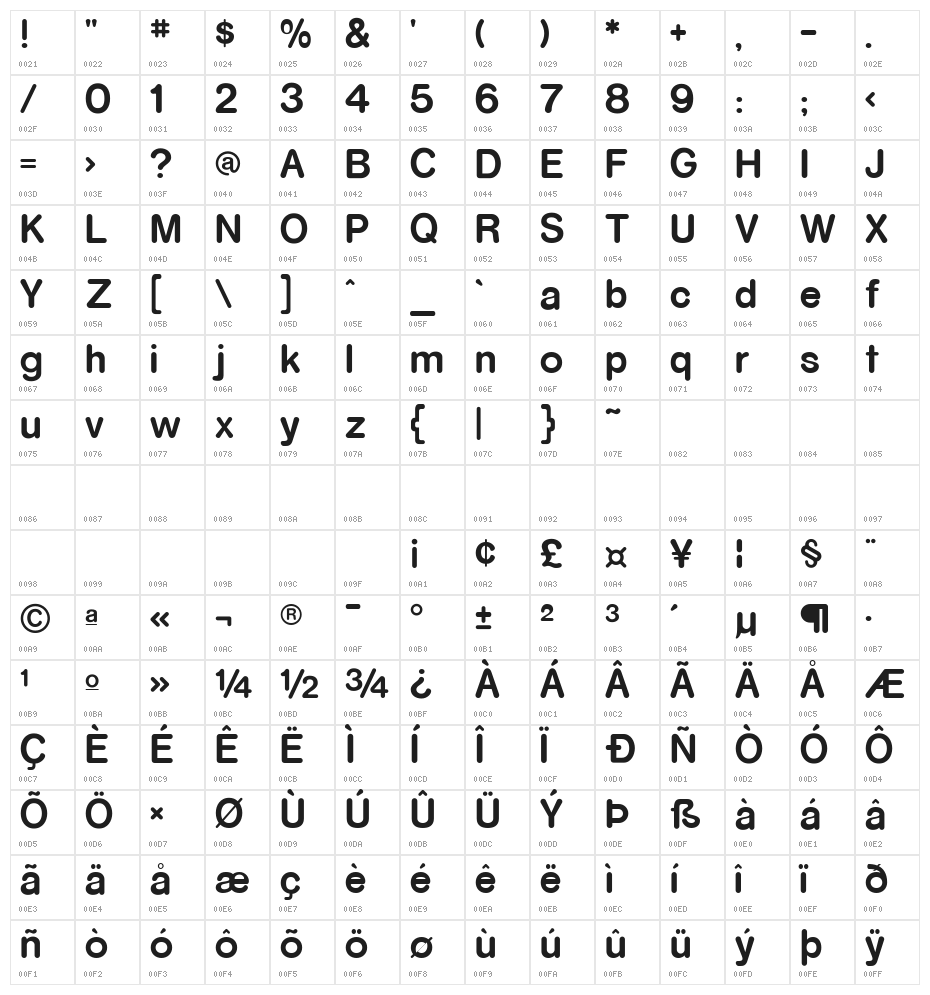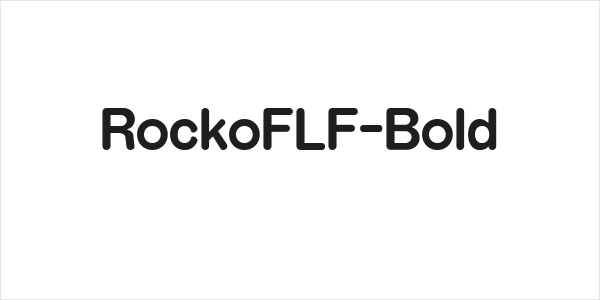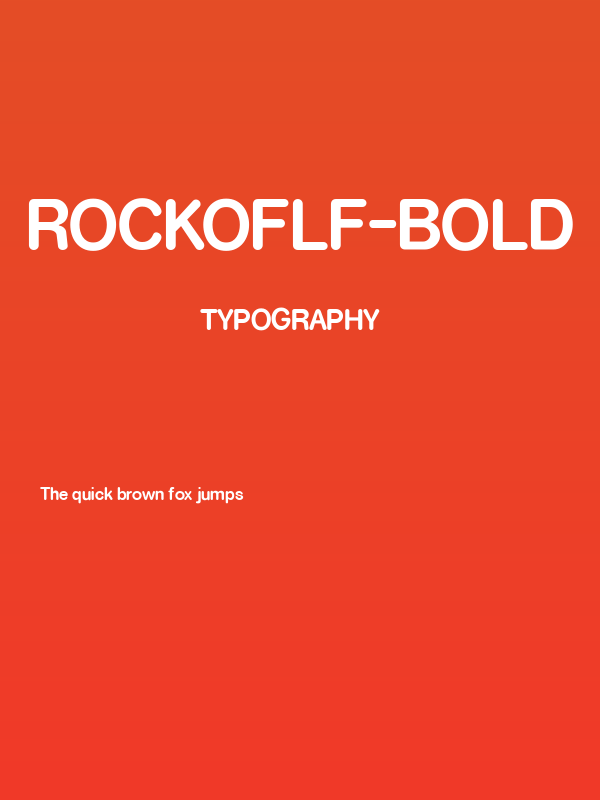
RockoFLF-Bold Font
| Anwendungsfall | Headlines, Logos, Branding |
| Vorgeschlagene Projekte | Ideal for branding, advertising, headlines, and digital content where a modern and approachable look is desired. |